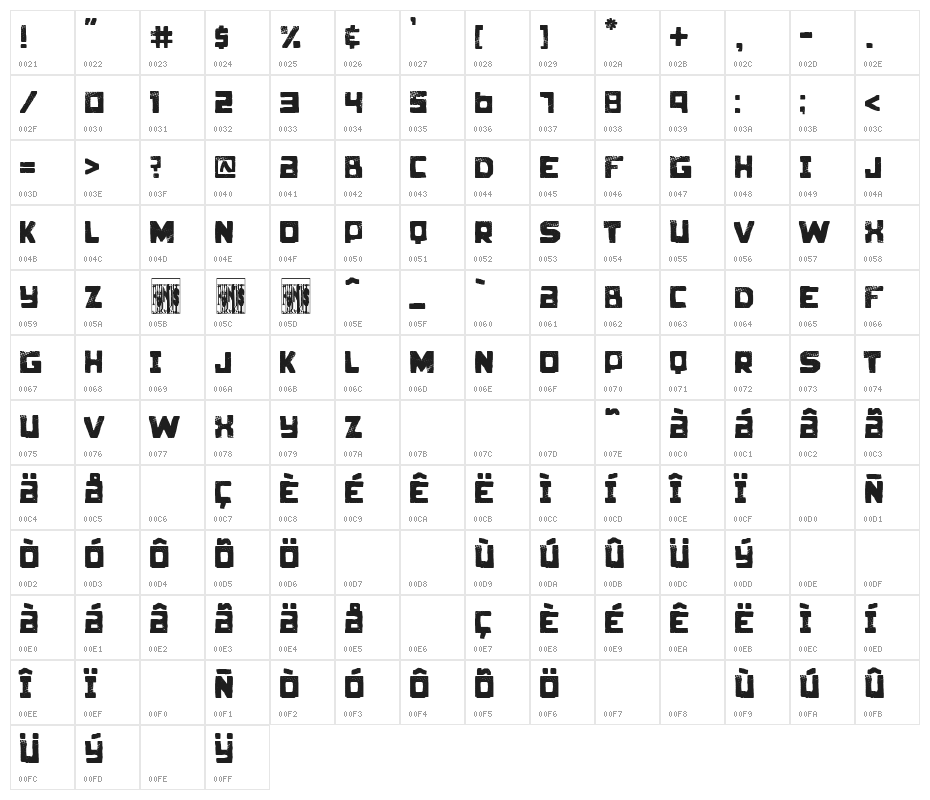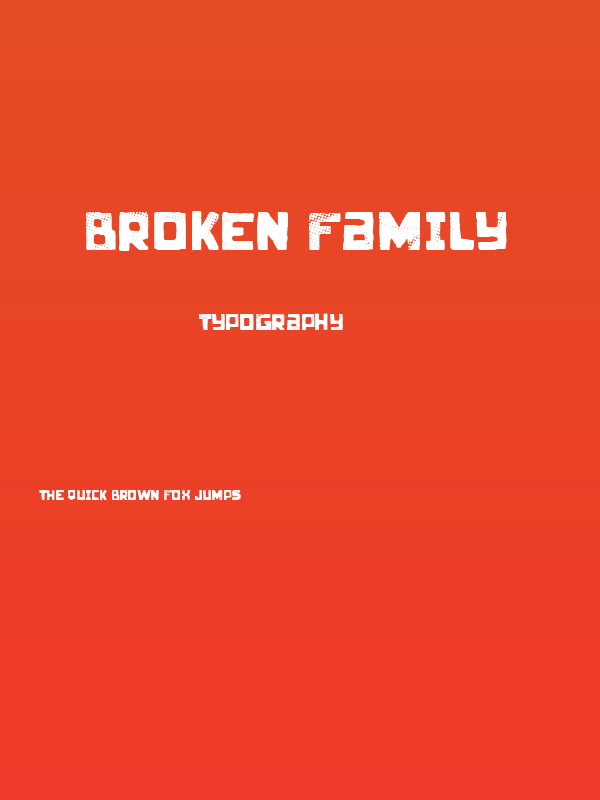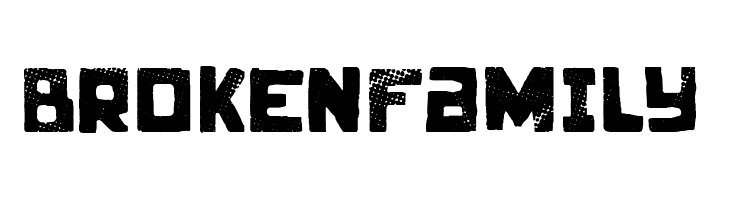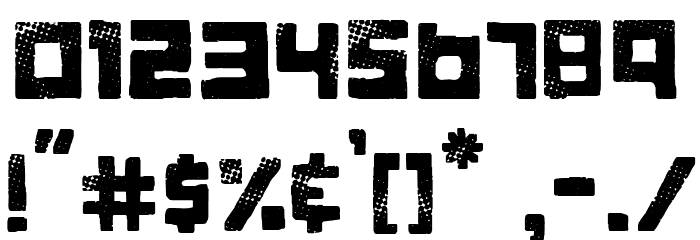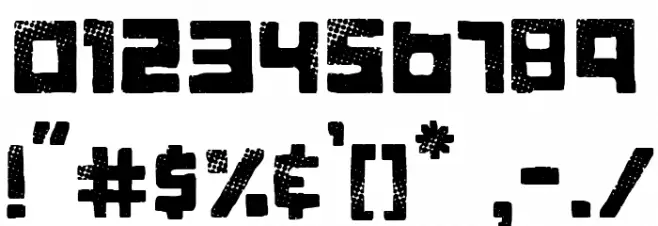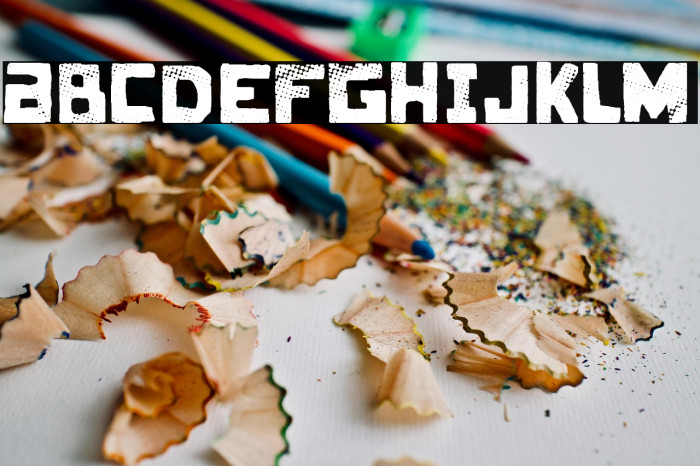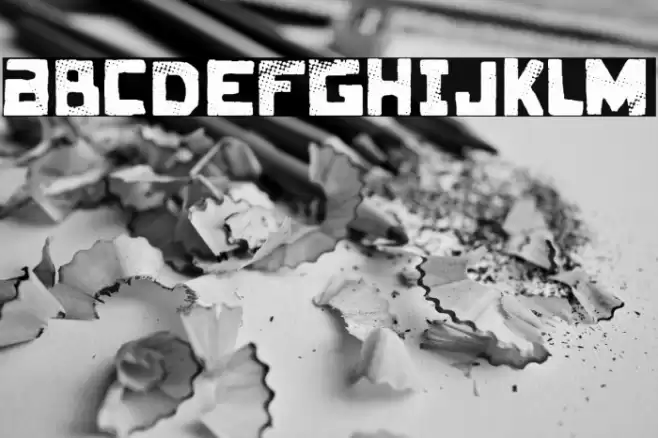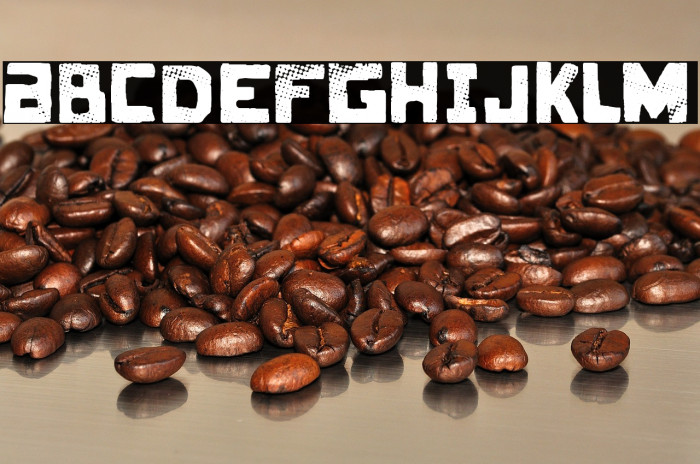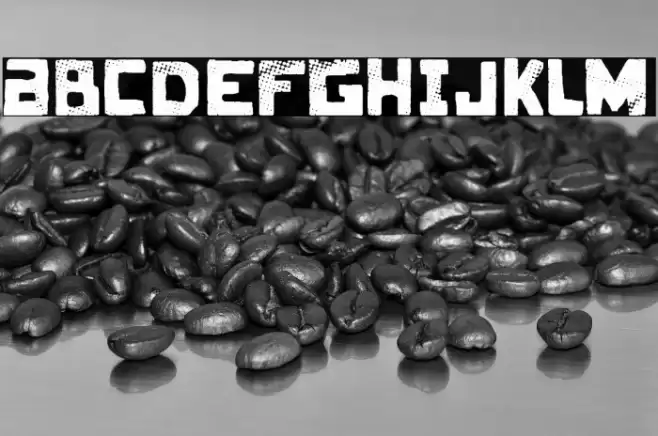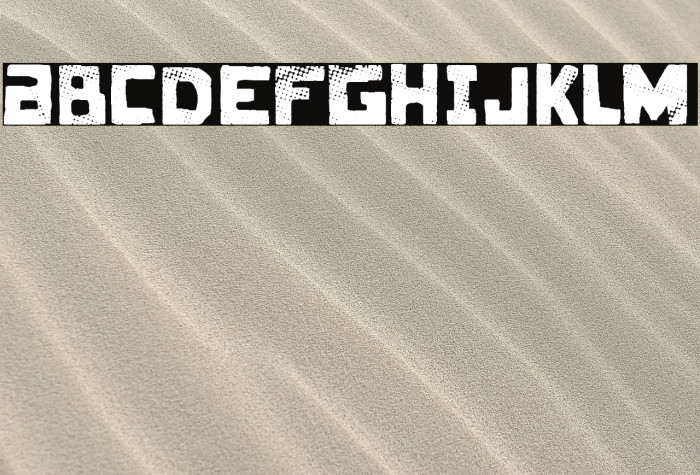
Broken Family Font
✎ Distorted Eroded
| Catégories | Distorted Eroded |
| Style général | Grunge, Decorative |
| Projets proposés | Ideal for posters, album covers, branding for edgy or alternative products, and any design needing a bold, gritty aesthetic. |